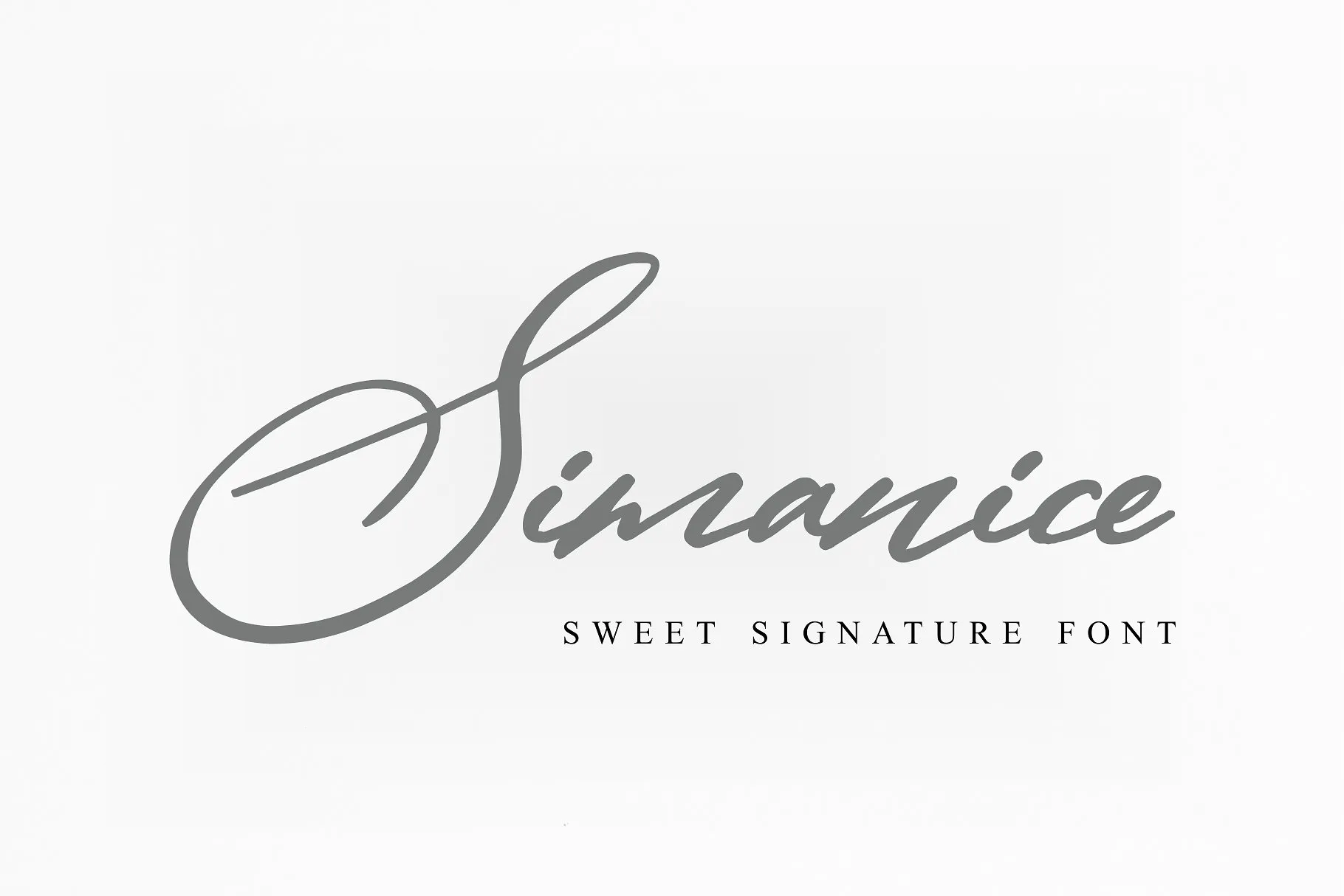
Simanice Signature Font – Fonte Grátis
Simanice Signature Font
Agradecemos pela atenção! Apresentamos a nova fonte assinatura elegante, intitulada Simanice Font. Esta fonte é um design contemporâneo e fashionista perfeito para complementar os outros elementos de sua identidade visual. Simanice é uma fonte de escrita que reflete seu nome: fluida e contemporânea. Esta opção de fonte gráfica vem para aperfeiçoar o aspecto de seus logos, marcas de imagem, revistas, blog posts, mídias sociais, anúncios e designs de produto. A Simanice Font não apenas é um complemento visual perfeito, mas também pode ser usada em uma variedade de formatos da vida contemporânea. Desde a criação de logotipos modernos até o estabelecimento de marcas de imagem sólidas, e do design de produtos ao nível da sua publicidade digital, esta fonte é um elemento indispensável para qualquer designer que busca trazer elegância à sua identidade visual. Estamos encantados em oferecer a você essa fonte única e poderosa. Simanice pode ser uma adição incrível ao seu arsenal de ferramentas gráficas.